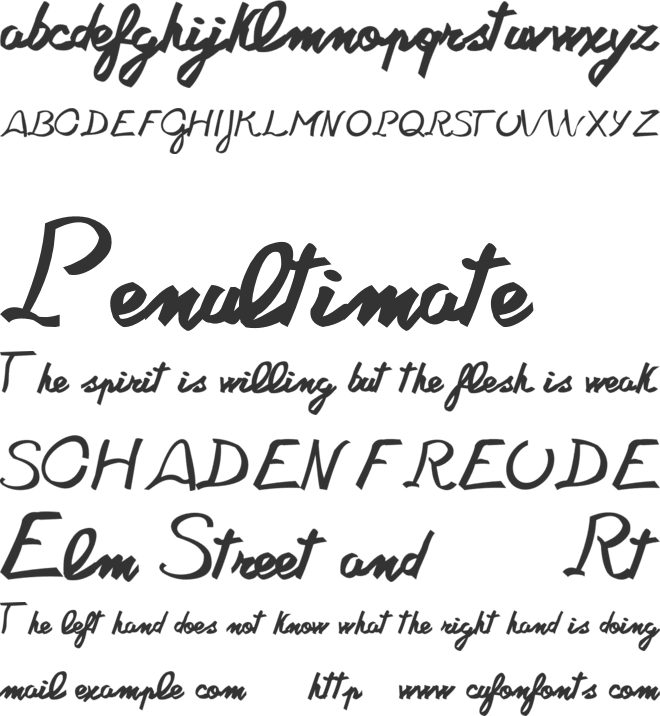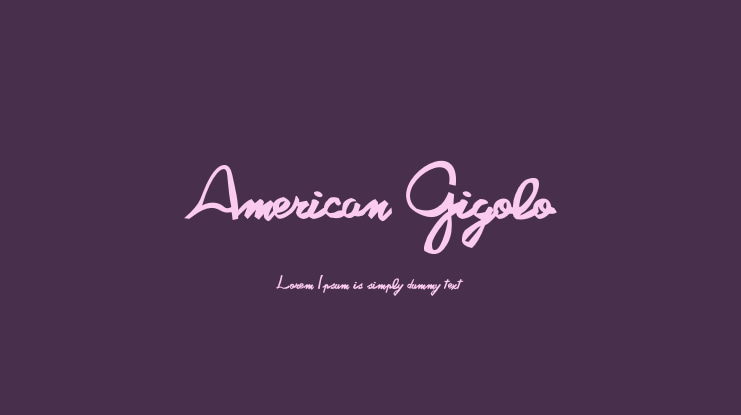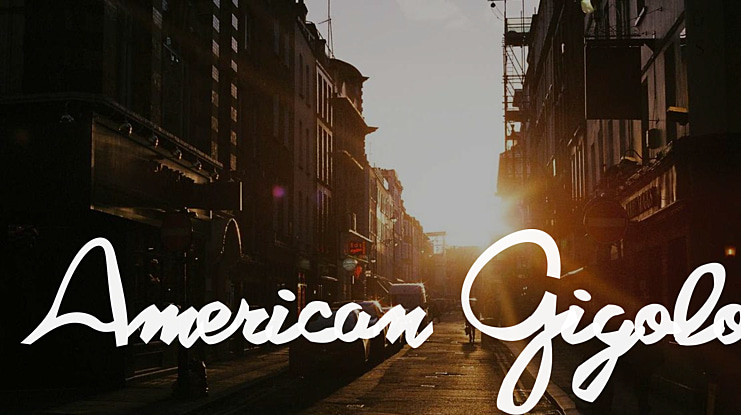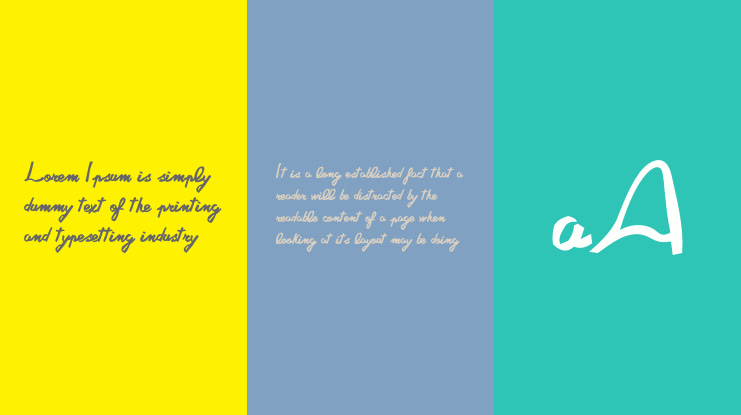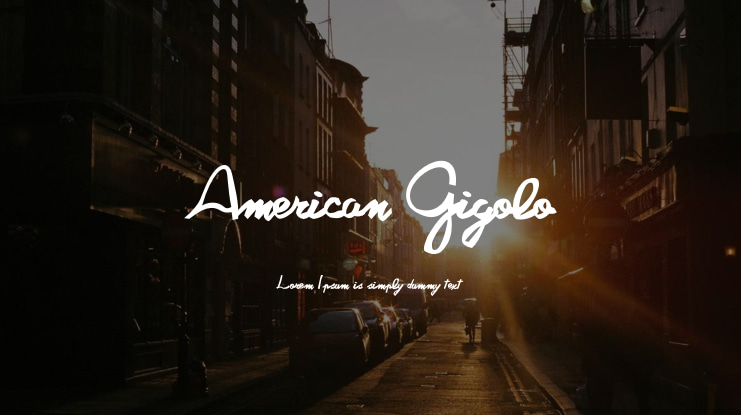
American Gigolo Font
P.A.Vannucci
AMERICAN GIGOLO font: direttamente dal film diretto da Paul Schrader e interpretato da Richard Gere, il font inedito per tutti gli estimatori del film. Da notare il ritocco necessario in Photoshop per conferire, alla titolazione, l'originale bordatura.
AMERICAN GIGOLO font: directly from the Best movie by Paul Schrader, with Richard Gere, the original font for all lovers. Use ADOBE Photoshop for the original border from title.